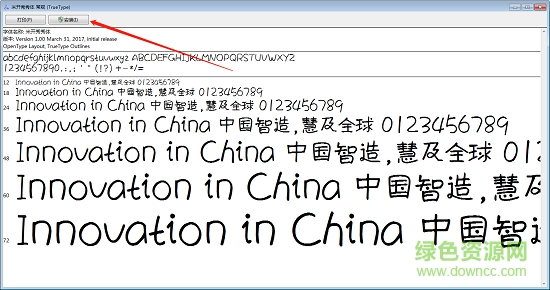
米開(kāi)秀秀體字體是一款充滿(mǎn)童趣的字體,字體的設(shè)計(jì)以簡(jiǎn)約為主,整個(gè)字體的形態(tài)類(lèi)似于小時(shí)候的寫(xiě)的字,帶有一點(diǎn)點(diǎn)的趣味,整個(gè)字體的排版看起來(lái)比較豐富,喜歡的用戶(hù)快來(lái)綠色資源網(wǎng)下載吧!
米開(kāi)秀秀體字體是一款ttf格式的手寫(xiě)字體。這款字體并不拘束,書(shū)寫(xiě)起來(lái)也沒(méi)有什么規(guī)律,但是從視覺(jué)效果上來(lái)看還稱(chēng)得上是整齊;而且它還有一點(diǎn)點(diǎn)的童趣,像是小學(xué)生書(shū)寫(xiě)數(shù)來(lái)的,很適合用在小孩的物品上。
米開(kāi)秀秀體字體美麗秀麗,在進(jìn)行書(shū)寫(xiě)的時(shí)候能夠帶給你十分整潔的視覺(jué)體驗(yàn),同時(shí)也可以運(yùn)用到廣泛的各類(lèi)媒體制作中哦!